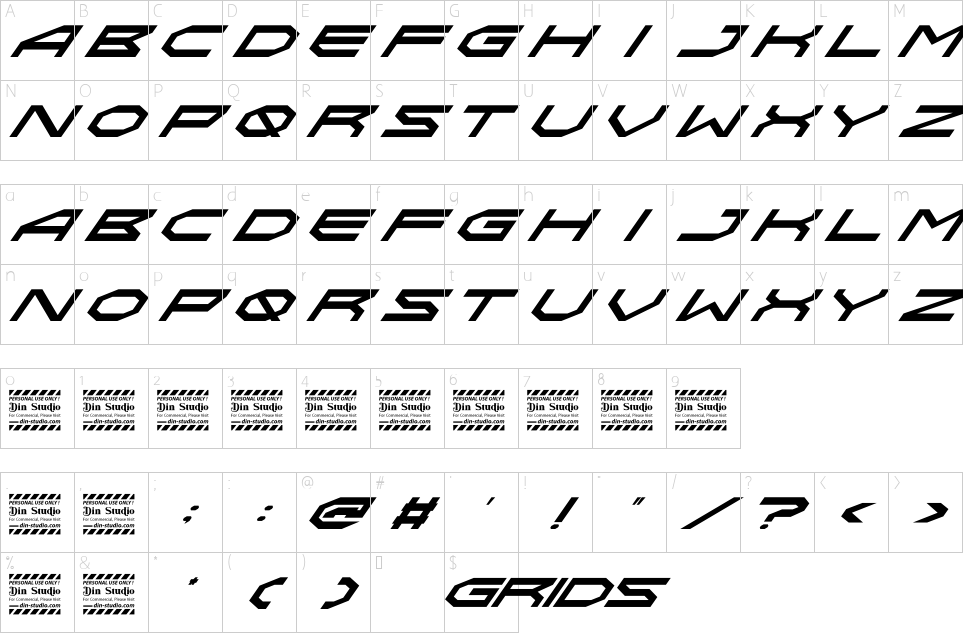
Grids Font – 1001 Free Fonts – Fonte Grátis
Grids é uma fonte minimalista e moderna que se destaca em qualquer design editorial ou digital. Essa elegante família de fontes vem em várias opções de estilos, desde linhas simples até gráficos mais elaborados, permitindo você criar designs variados com facilidade. Desenvolvida pela Din Studio, Grids foi projetada para dar um toque clean e sofisticado a qualquer projeto. Com uma arquitetura minimalista que se destaca perfeitamente no design de websites, gráficos ou editoriais digitais, essa fonte oferece uma combinação única de simplicidade e força. O fato de ter sido baixada 1.952 vezes é um testemunho do seu valor e popularidade entre os designers. Navegue pela família Grids e descubra por si mesmo porque essa fonte se tornou uma opção favorita para muitos criadores de conteúdo.